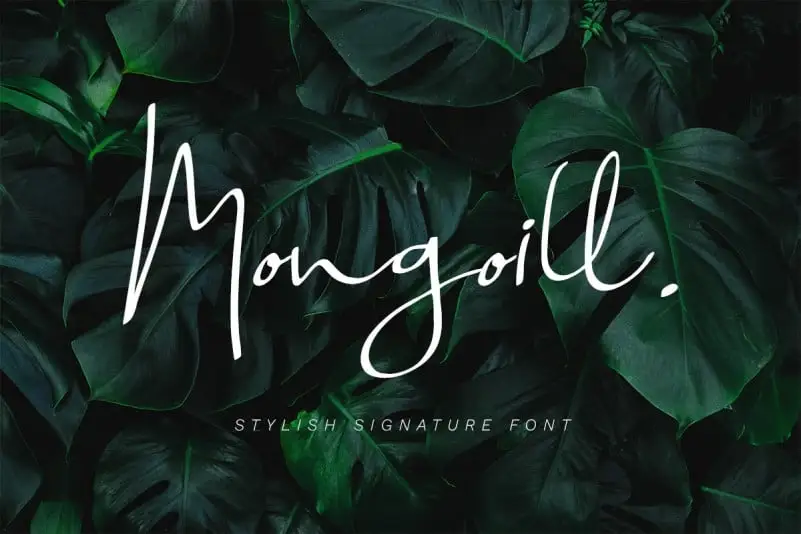
Aqui está uma descrição envolvente para a página de download da fonte ‘Mongoill Handwritten Font’, seguindo as instruções: Através do projeto inovador dos designers da 99designs, surge a novíssima ‘Mongoill Handwritten Font’. Esta moderna tipografia script escrita a mão é perfeita para projetos de marca, logotipos, designs para casamentos, postagens nas redes sociais e anúncios. Ideal também para embalagens de produtos, designs de produtos, etiquetas, fotografias, watermarks, convites e materiais de correspondência – este ‘Mongoill Handwritten Font’ combina elegância com rusticidade, oferecendo uma opção perfeita para qualquer projeto que necessite de um toque agradável e sofisticado.